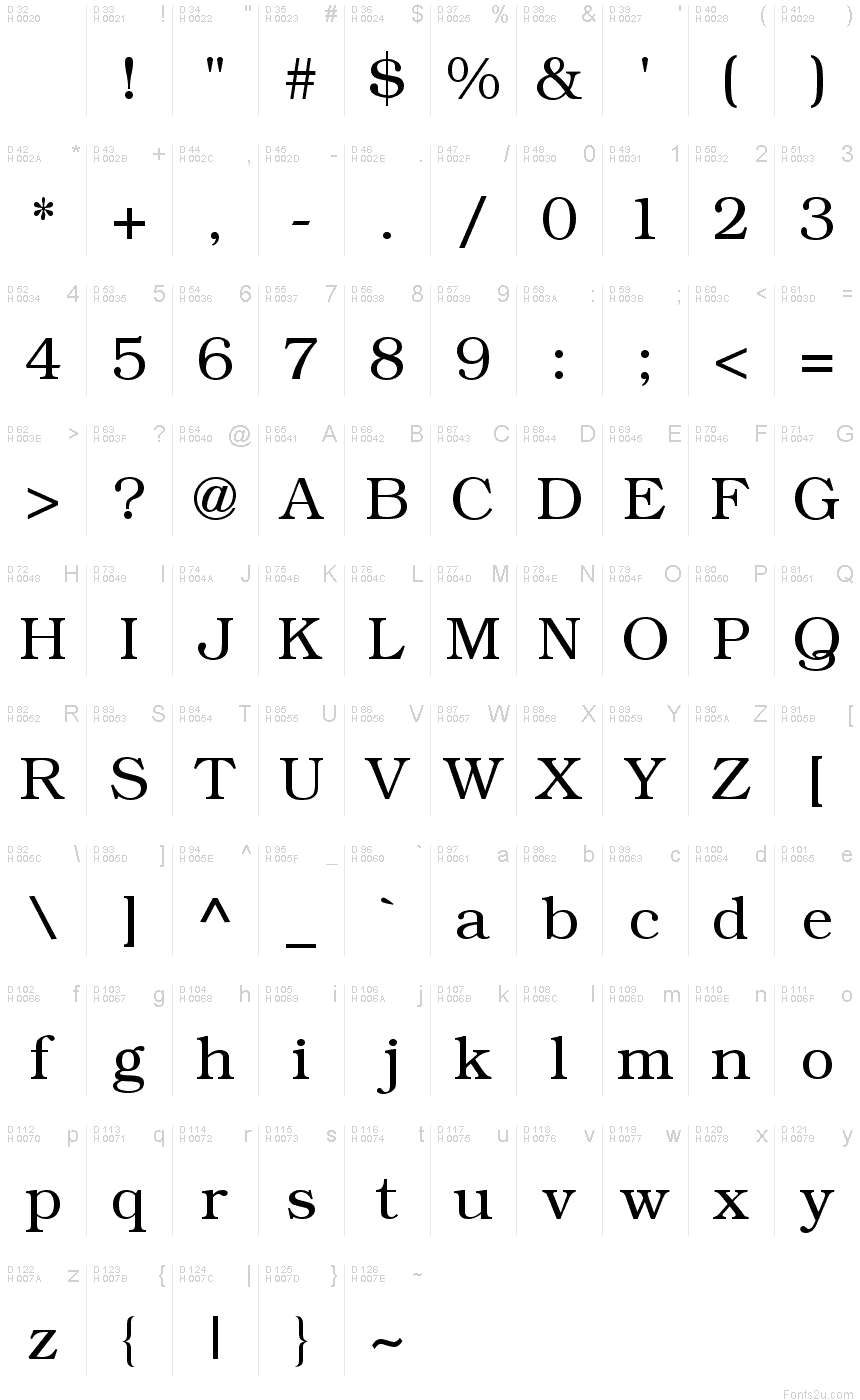
ER Bukinist 866
ER Bukinist 866 autorstwa Gavina Helfa to bezpłatny, klasyczny krój szeryfowy o literackim charakterze i wyglądzie przypominającym druk na papierze: ma solidne trzonki, ostre szeryfy w kształcie klina oraz krągłe, pewne siebie krzywizny, niczym wyjęte z ulubionego katalogu. Jest autorytatywna, lecz nie chłodna – dzięki temu tekst zachowuje swój ciepły wyraz, pozostając przy tym przemyślanym i starannie zaprojektowanym.
ER Bukinist 866 świetnie sprawdzi się na okładkach książek, w składach redakcyjnych, na plakatach literackich, w brandingu butikowym, programach muzealnych, opakowaniach oraz oznakowaniach, gdzie czytelność musi iść w parze ze stylem. Ten darmowy font najlepiej prezentuje się, gdy ma trochę przestrzeni; w przypadku podpisów lub tekstu uzupełniającego zestaw go z dyskretnym krojem bezszeryfowym, takim jak Inter lub Helvetica.